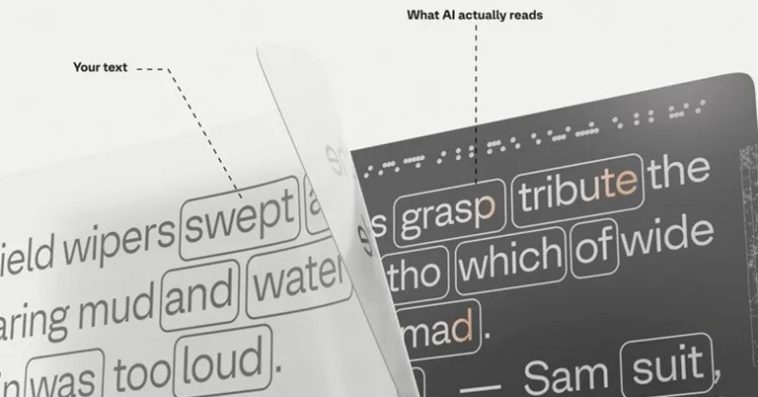
ხელოვნური ინტელექტის მიერ ვებსაიტებიდან კონტენტის მასობრივად შეგროვების წინააღმდეგ კიდევ ერთი საინტერესო ინსტრუმენტი გამოჩნდა. ბრაზილიურმა კრეატიულმა სტუდიამ Seneda & Abrucio და დანიურმა ტიპოგრაფიულმა კომპანიამ Playtype შექმნეს ShieldFont – უფასო, ღია კოდის მქონე შრიფტი, რომელიც ადამიანისთვის ჩვეულებრივად იკითხება, თუმცა AI-სთვის ტექსტის მნიშვნელობას ცვლის.
ShieldFont OpenType-ს სპეციალურ ფუნქციას იყენებს, რომლის მეშვეობითაც HTML-ის კოდში გარკვეულ სიტყვებს სხვებით ანაცვლებს. შედეგად, ადამიანი ეკრანზე მაინც სწორ ტექსტს ხედავს, ხოლო AI-სკრაპერები შეცვლილ ვერსიას კითხულობს. წინადადებები გრამატიკულად გამართული რჩება, თუმცა მათი შინაარსი იცვლება, რაც AI-ს სასწავლო მონაცემებს „აბინძურებს”.
პროექტის მიზანი AI-ს წინააღმდეგ ბრძოლა არ არის. მისი ავტორები მიიჩნევენ, რომ ინტერნეტში კონტენტის გამოქვეყნება არ ნიშნავს, რომ კომპანიებს მისი თავისუფლად გამოყენების უფლება აქვთ საკუთარი მოდელების გასაწვრთნელად. მათი აზრით, არსებული მექანიზმები, როგორიცაა, მაგალითად, robots.txt, ხშირად იგნორირებულია, ამიტომ საჭირო იყო ისეთი გადაწყვეტა, რომელიც თავად კონტენტის დონეზე იმუშავებდა.
ShieldFont ეფუძნება Playtype-ს უკვე არსებულ შრიფტ Optik-ს და ექვსი სხვადასხვა ფორმით არის ხელმისაწვდომი. ამასთან, პროექტი მხოლოდ ერთ შრიფტს არ მოიცავს, მას თან ახლავს ინსტრუმენტებიც, რომლებიც დიზაინერებსა და დეველოპერებს საშუალებას აძლევს, იგივე ტექნოლოგია საკუთარ შრიფტებშიც გამოიყენონ.
ტესტირების მიხედვით, ShieldFont-ით დაცული ტექსტების დაახლოებით 56%-ში AI უკვე განსხვავებულ ფაქტობრივ ინფორმაციას იღებს, რაც ნიშნავს, რომ ასეთი კონტენტი AI-ს სასწავლო მონაცემების სანდოობას ამცირებს.
პროექტის ავტორები აღიარებენ, რომ ShieldFont სრულყოფილი დაცვა არ არის. თუ ვინმე კონკრეტული ვებსაიტის მიზანმიმართულ ანალიზს დაიწყებს, სისტემის გვერდის ავლა შესაძლებელია. თუმცა მასობრივი „სკრაპინგისთვის” ეს დამატებით ბარიერს ქმნის, ზრდის პროცესის სირთულესა და ხარჯს, რაც AI-კომპანიებისთვის კონტენტის ავტომატურად შეგროვებას მნიშვნელოვნად ართულებს.